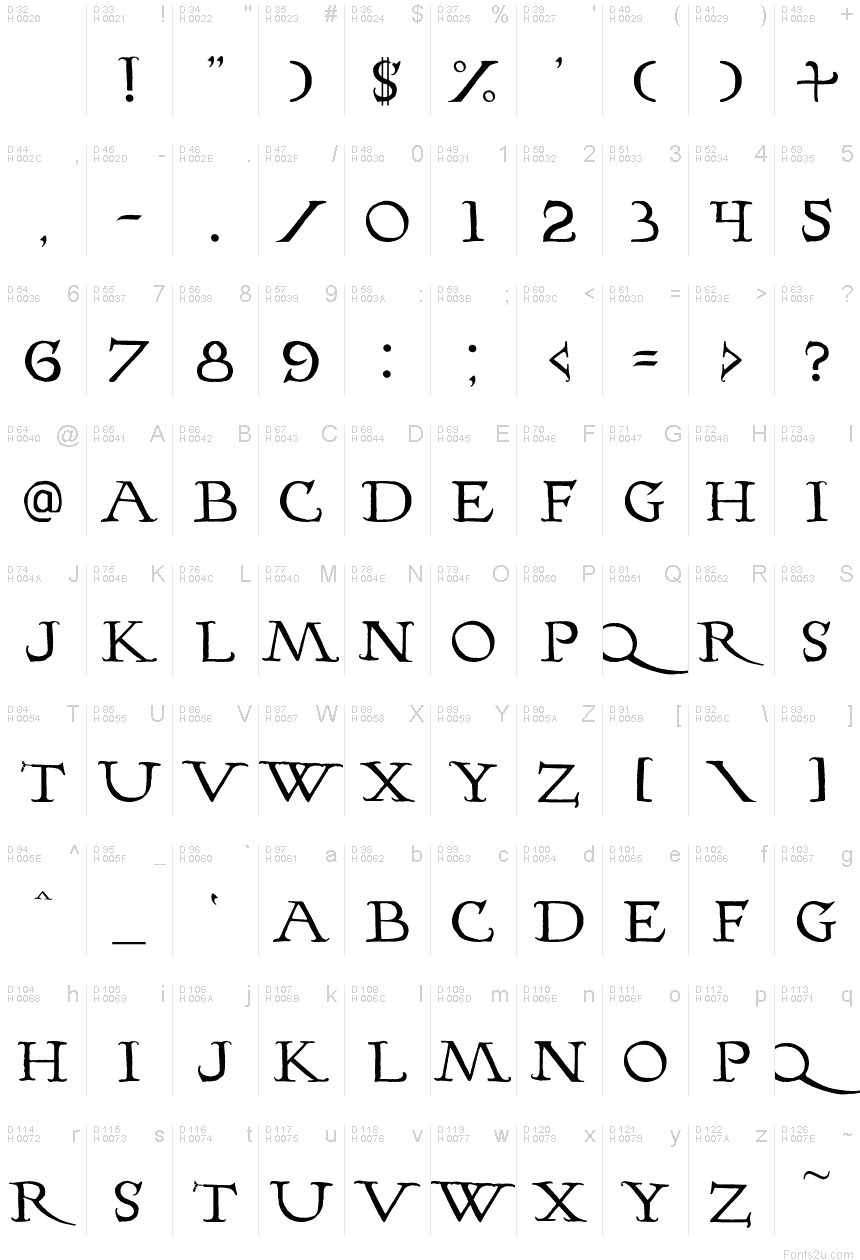
Písmo Hopfer Hornbook od Staffana Vilcansa je bezplatné retro patkové písmo, které působí, jako by bylo vytaženo přímo ze starého dřevořezu nebo historické učebnice. Písmena mají inkoustové, nepravidelné okraje a lehce roztřesené kontury, takže každé slovo vypadá jako ručně vytištěné, nikoliv digitálně vyražené. Textura dodává jemný efekt popraskání, který titulům a logům okamžitě propůjčuje nádech starých časů, folklóru a tajemna.
S písmem Hopfer Hornbook dodáte knižním obálkám, historickým plakátům, folkovým či metalovým albům, fantasy hrám, muzejní grafice nebo vintage obalům bohatý a hmatatelný charakter. Rozestupy zůstávají čitelné i při větších velikostech, kde drsné obrysy skutečně vyniknou. Tento bezplatný font skvěle funguje v kombinaci s čistým bezpatkovým písmem pro hlavní text – nechte Hopfer Hornbook vyniknout v nadpisech, zatímco bezpatkové písmo zajistí klidný a jasný doprovodný text.